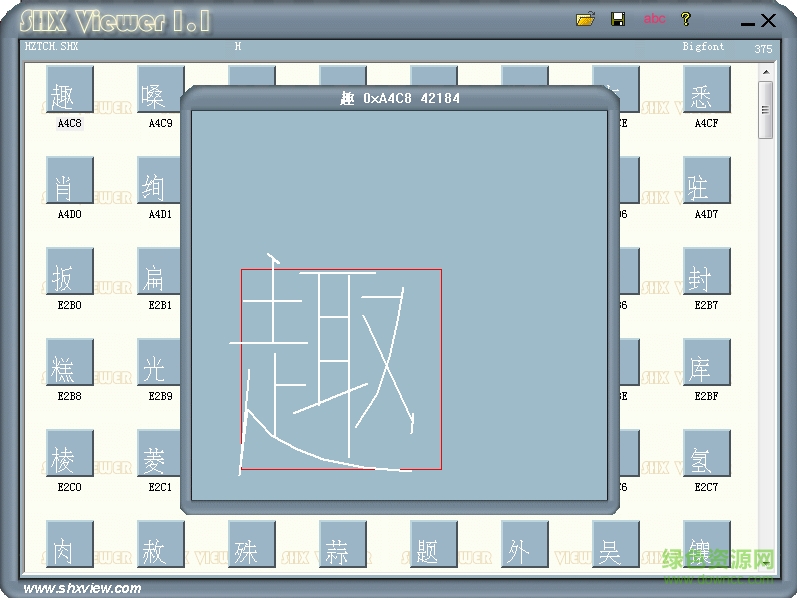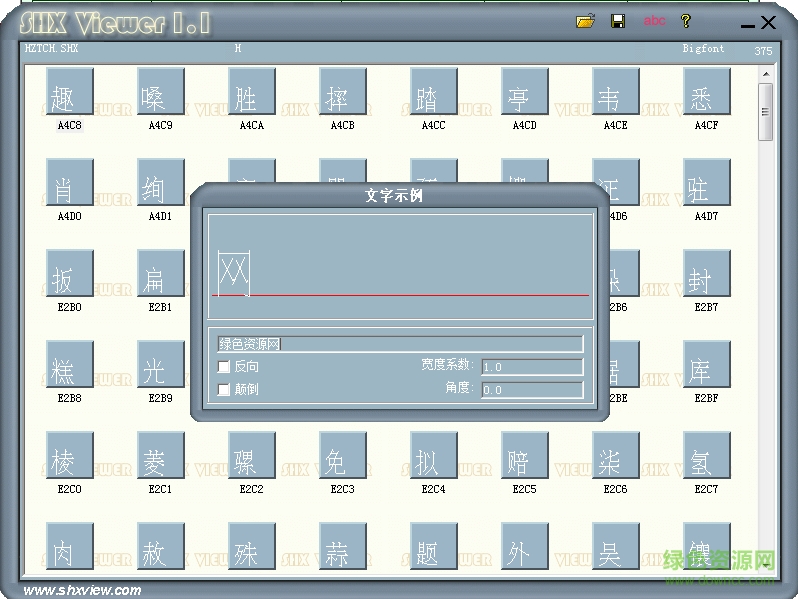
hztch.shx是一款擁有375個(gè)字符的cad大字體,有著簡(jiǎn)潔清晰的行筆,字形大方嚴(yán)謹(jǐn),讓你的平面設(shè)計(jì)、排版印刷更具美感,綠色資源網(wǎng)誠(chéng)意推薦!
hztch.shx是一款cad字體,字體不是很完整,已有的字庫(kù)造型優(yōu)雅娟秀,有著印刷式的美感,如果您喜歡,來(lái)綠色資源網(wǎng)下載吧!